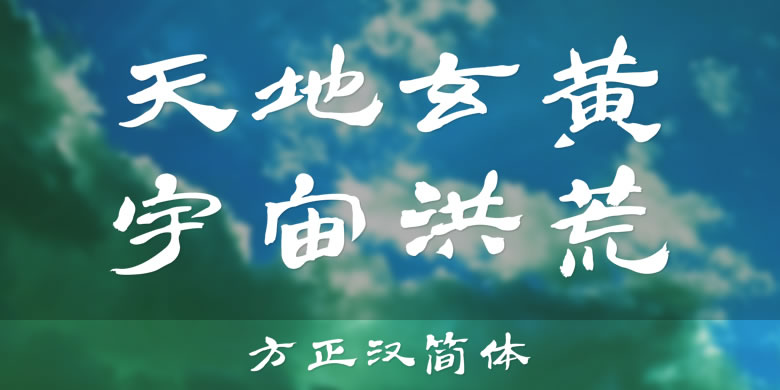
品牌:方正字库设计师:张有清发行时间:2007字库编码:大陆简体(GB2312-80)分类:常规书写·毛笔
方正汉简由书法家张有清先生创作。这款字体源于汉简帛书,用笔轻松率意,点画放纵,笔画刚劲,结体灵动多变。其个性奔放飘逸,带有一种朴拙之美,适用于文化类的宣传设计,以及商业类品牌的广告和产品包装设计。